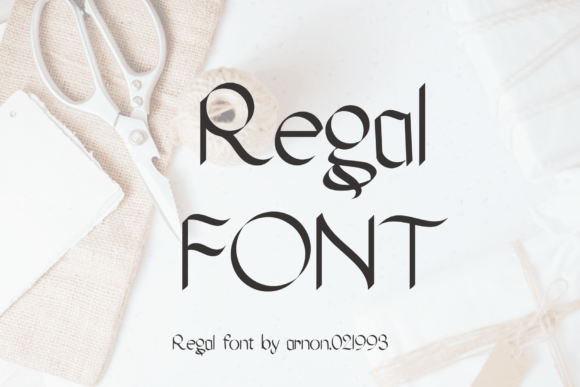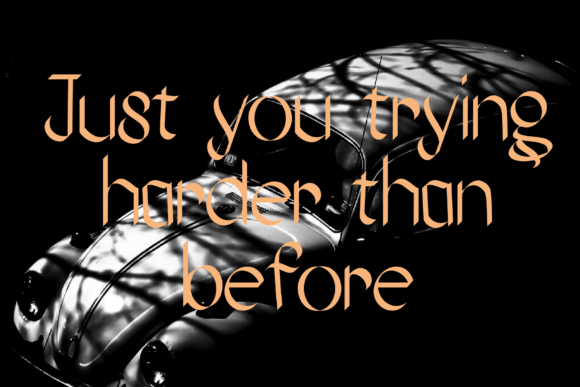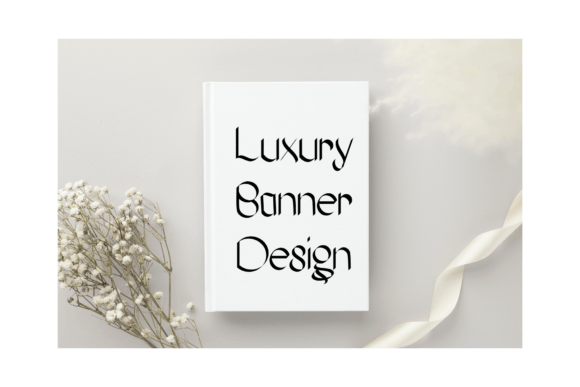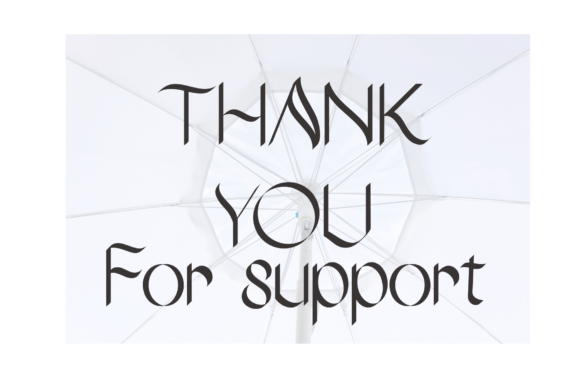
فونت Regal انگلیسی
| ⭐ توضیحات | این فونت برای پروژه عروسی، کارت تبریک، آرم، کارت ویزیت مواد باند، نقل قول، پوستر، پیراهن، لیوان و موارد دیگر بسیار زیبا است! |